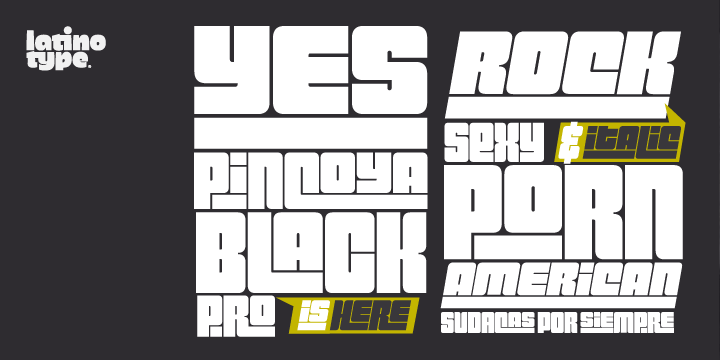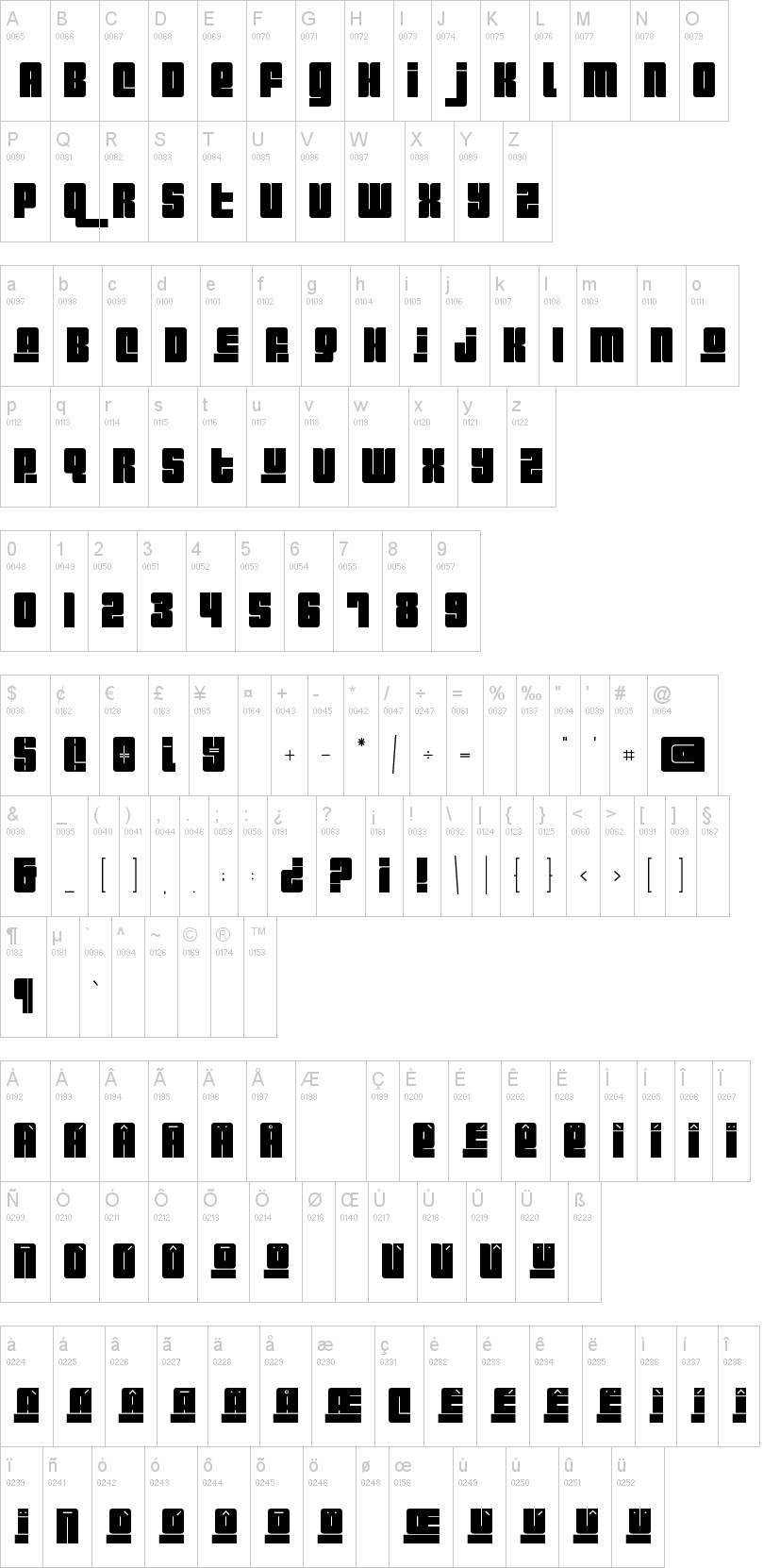
Note of the authorPincoya Black es una fuente experimental inspirada en el lettering de un afiche de la guerra civil española y con una fuerte influencia de la tipografía llanquihue de Francisco Galvez. Pincoya es una fuente unicase, pero con la opción de variar en los caracteres vocales, los cuales se integran a los caracteres consonantes.